近年来,我们不难发现,越来越多的品牌在进行品牌视觉形象重塑时,都会涵盖“品牌定制字体”这一项设计。
例如,在GrayDesign不久前分享的7-Eleven、欧莱雅、标致汽车……等等案例中都有包含定制字体的部分,几乎已经成为了各大品牌视觉形象升级的“标配项目”。
不过,不知道你又是否知道,其实现在有很多城市都已经定制设计了专属于该城市的“城市字体”?
为此,本文将特别为你分享来自不同国家的3款“城市字体”案例:
瑞典·斯德哥尔摩
Stockholm Type
首先要为你介绍的是瑞典斯德哥尔摩的“Stockholm Type”,斯德哥尔摩(Stockholm)是瑞典的首都和第一大城市,也是瑞典国家政府、国会以及皇室的官方宫殿都所在地。
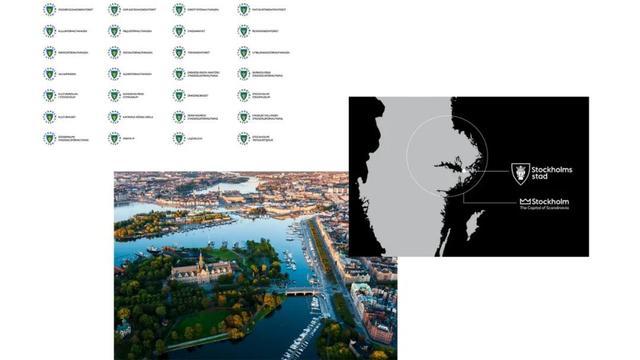
2012年,为了提升城市形象,当地政府将斯德哥尔摩原本各个部门不同的现象合并为一个品牌,并为其进行品牌形象重塑。
由品牌设计公司Essen International操刀,通过前期的策略设定,标志设计升级、环境视觉改造以及定制字体设计等等,为斯德哥尔摩打造一套城市专属的视觉语言。
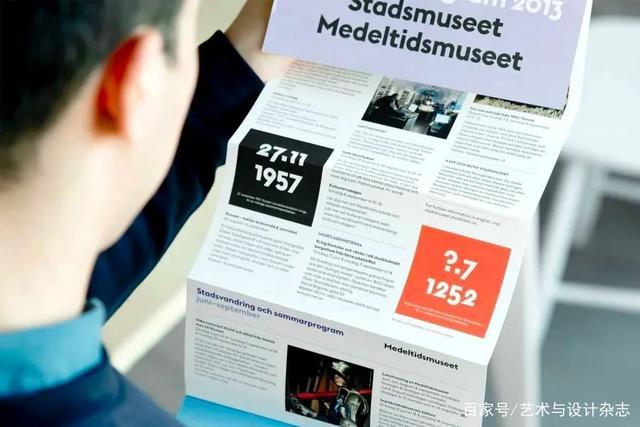
日本·名古屋市
金シャチフォント
另一款要为你介绍的,也是本文介绍的案例中“定制度”最高的一款城市字体。
“金シャチフォント”字体是一套融合了名古屋传统文化象征的明朝体(即:我们常说的宋体)。
金シャチ(金鯱,在日本通常表示一种海兽的名字),负责这一款字体设计的Type Project团队将位于名古屋市的城堡「名古屋城」屋顶上这个虎头鱼身的“金鯱”装饰,以及日式建筑的曲线造型融入字体的笔画细节之中,最终设计出这一款装饰性极强的明朝体。
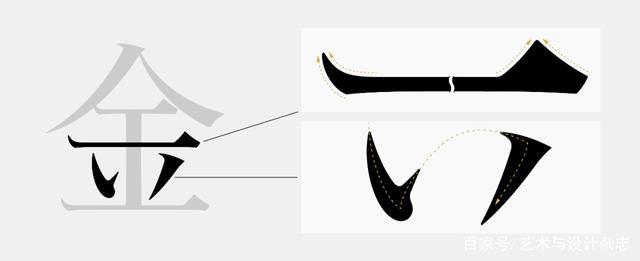
据了解,早在2009年,这一款城市字体的构想就已启动。并在名古屋开府400年(即:2010年),正式发表了“金シャチフォント”字体的原型样张。
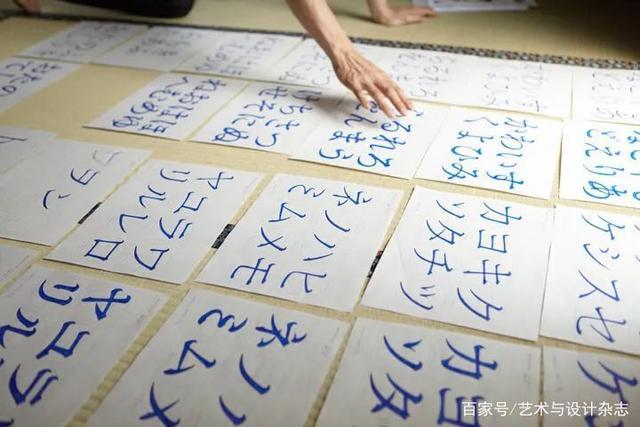
直到2020年3月,这一款“金シャチフォント姬”字体才正式公开发售。与此同时,目前Type Project团队还在推进同系列的“金シャチフォント殿”字体的开发工作。
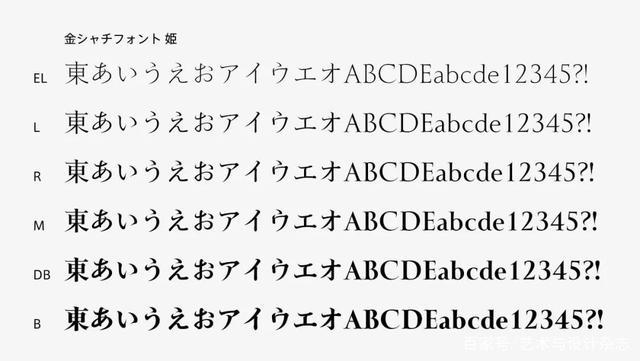
除此之外,“金シャチフォント姬”字体的假名部分,也结合了名古屋方言并加入了独特的表达方法,例如「みゃ~、りゃ~」这类词组合成“连字”,希望以此唤起民众对于该城市的认同感。
目前上市的“金シャチフォント姬”字体包含6种不同字重,使其可以广泛应用于各种不同的使用场景。
西文字体的部分还特别仿照古罗马大写字母的比例,并融入相应的装饰性元素,使整体呈现出古典且华丽的风格。
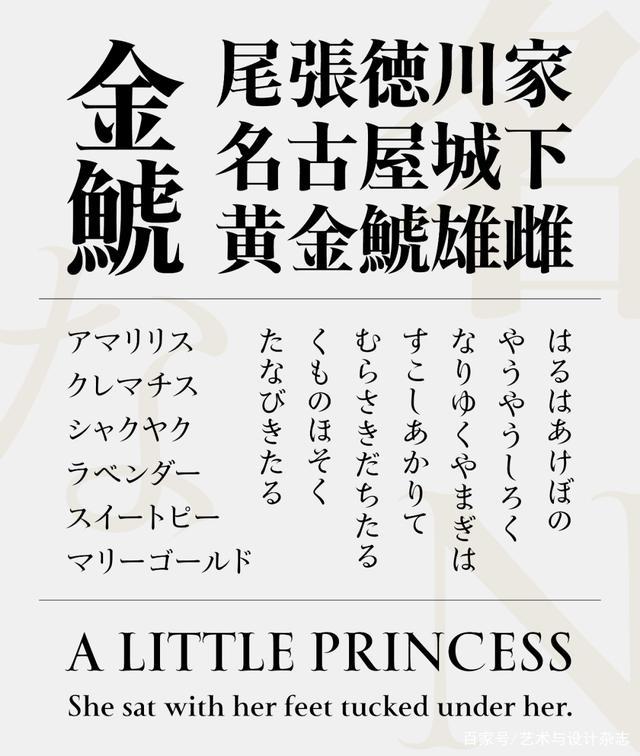
韩国·首尔市
汉江体+南山体
另一款要为你介绍的是,同样为了普及、提升首尔城市品牌形象和品牌价值,韩国首都首尔市推出的首尔城市字体系列。
分别为:宋体系列的“首尔汉江体”、以及黑体系列的“首尔南山体”。不仅包含常规体和窄体共计19种字体,而且这套字体还开放授权“任何人均可免费下载并自由使用于视频、印刷、网站、移动设备等各种媒介中,而无需特殊许可程序”。
“首尔汉江体”字体特征
“首尔南山体”字体特征
据官方介绍:“这2款「城市字体」以首尔最具代表性的资产「汉江」与「南山」命名,将提高韩民族固有美丽语言——韩文的文化自豪感魂字。”